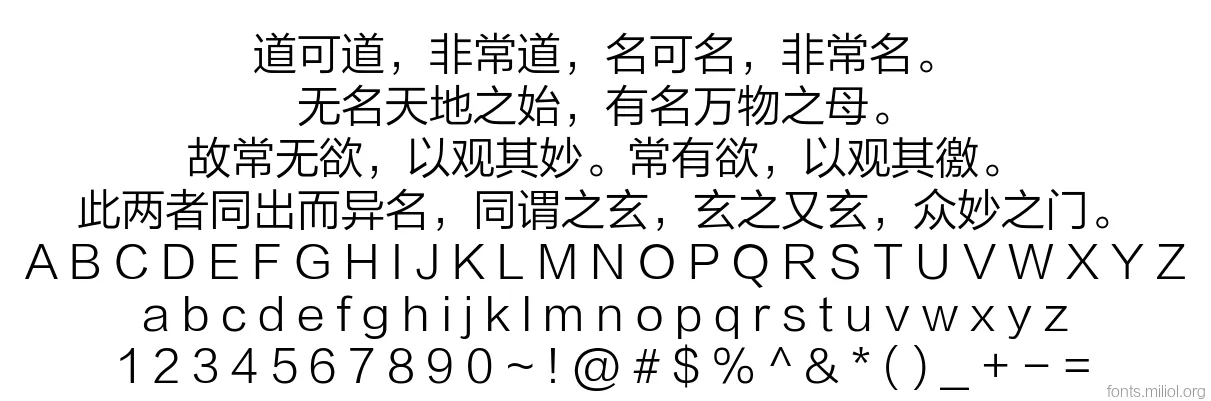
**方正兰亭细黑简体:优雅现代的字体选择**
方正兰亭细黑简体(FZLanTingHeiS-L-GB)是一款兼具现代感与优雅气质的字体,由方正字库精心设计。其笔画纤细流畅,结构匀称,整体风格简洁而不失精致,适合用于标题、广告、品牌设计等多种场景。
这款字体以黑体为基础,融入了细腻的笔触调整,使文字在清晰易读的同时更具设计感。无论是印刷品还是数字媒体,方正兰亭细黑简体都能为内容增添专业与时尚的视觉效果。
方正兰亭细黑简体 字体映射图